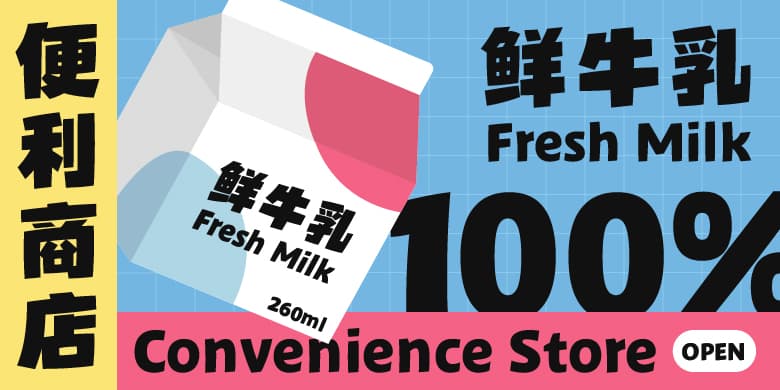
品牌:方正字库设计师:刘汉旭发行时间:2021字库编码:大陆简体(GB2312-80)分类:创意字体字体属性:精品字
方正拙黑以黑体为基础,笔画以方形为主,向右上倾斜的姿态与粗壮的笔画,相映成趣,形成一种块面感强、亦方亦圆的整体态势,给人以自然、稳健、敦厚、古拙之感,故名“拙黑”。适用于广告标题、产品包装、影视海报等应用场合,此外,字体呈现出的日式感,用在与日本文化相关的场景也很适合